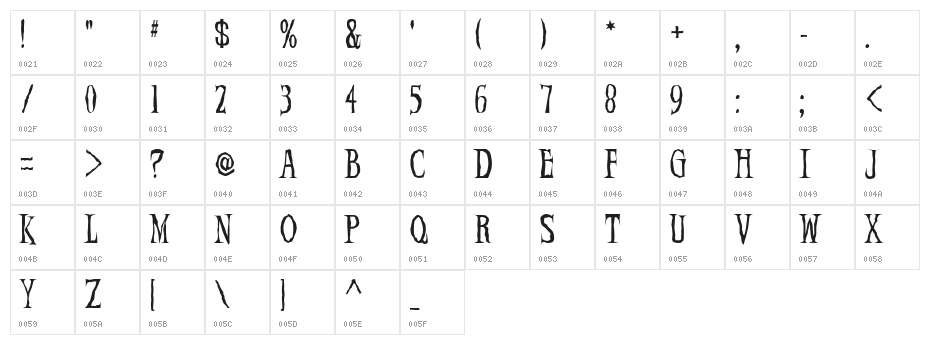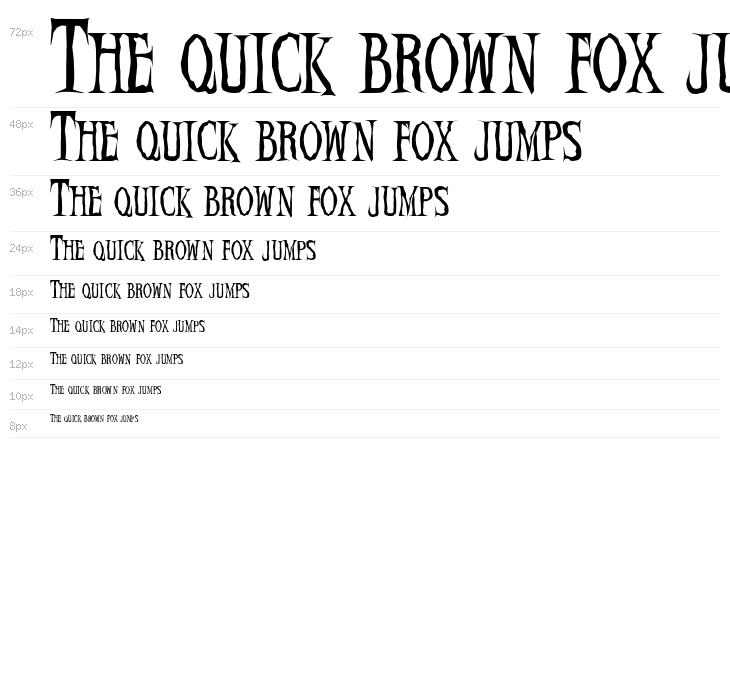
Demon Night Font
✎ Gothic
| Gesamtstil | Gothic, Dramatic, Eerie |
| Anwendungsfall | Headlines, Logos, Themed Events |
| Vorgeschlagene Projekte | Ideal for horror-themed designs, Halloween promotions, and mysterious or dark creative projects. |